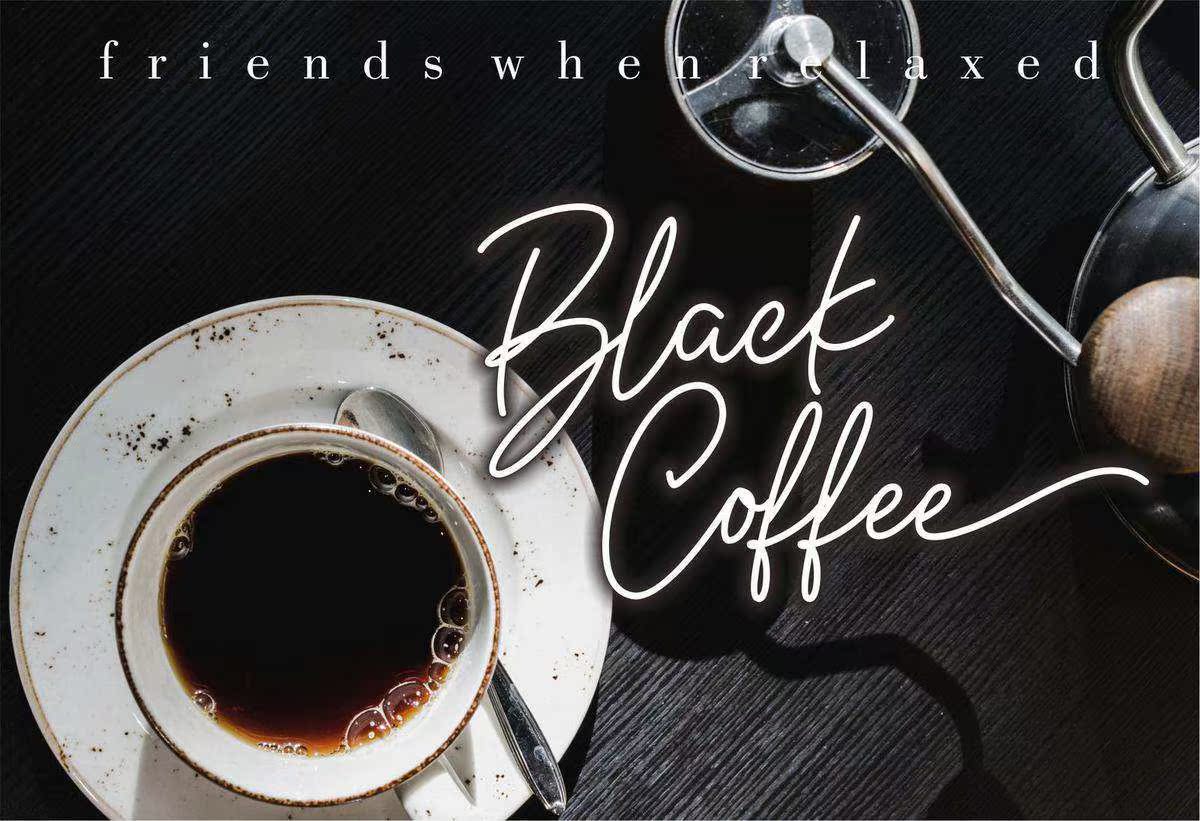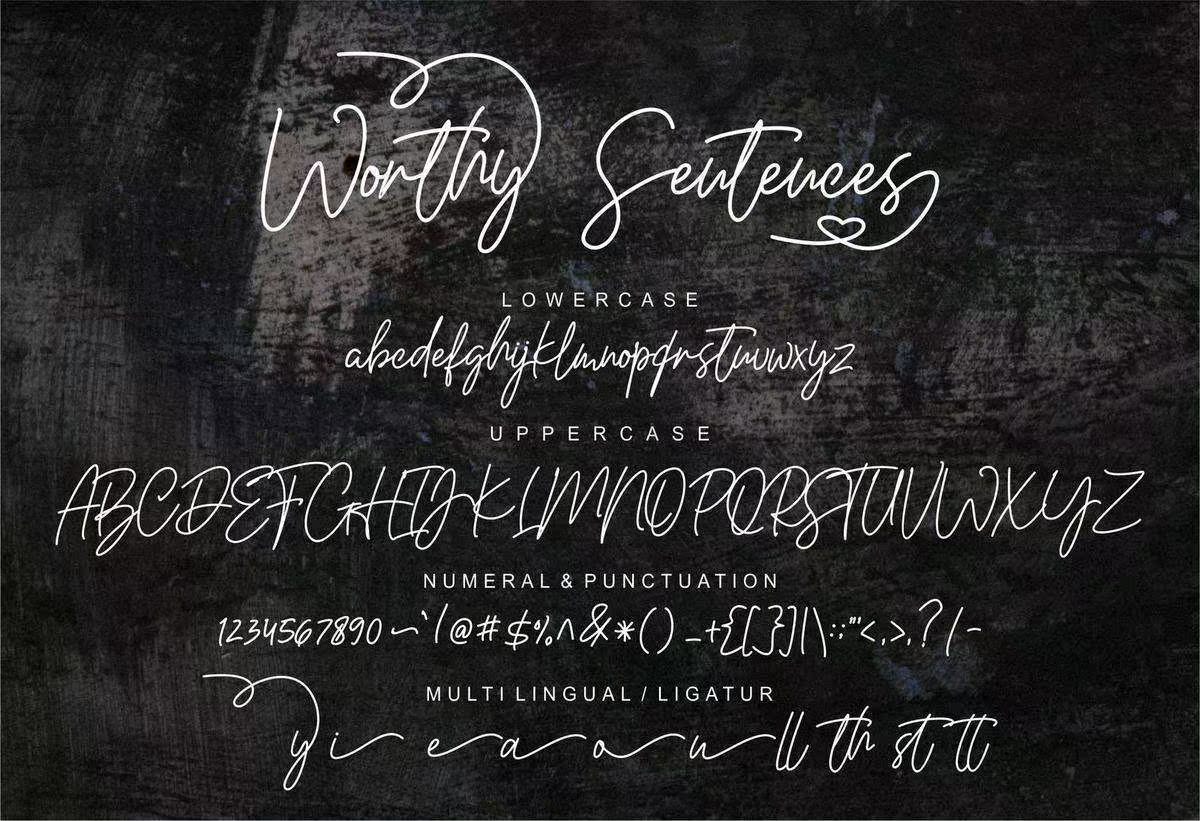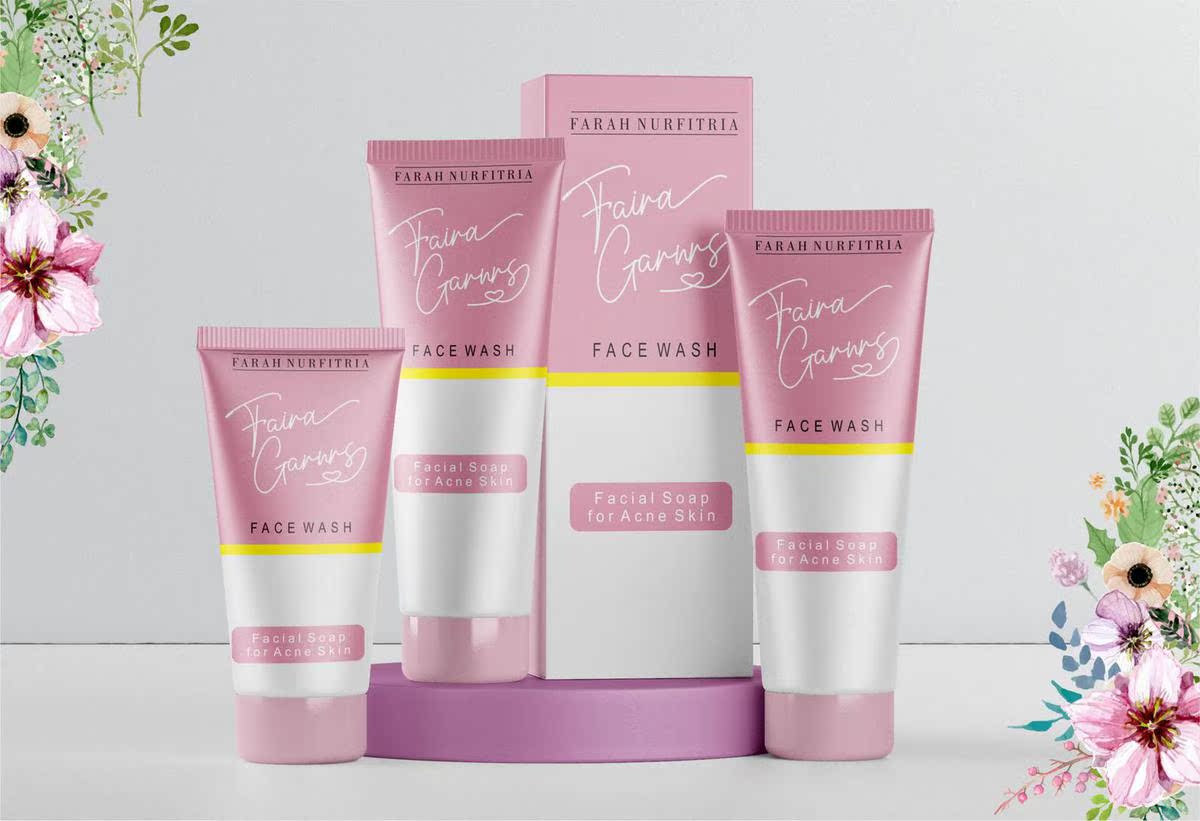
有价值的内容是直接使用鼠标的,使此字体外观完美,具有签名风格,此字体适用于看起来优雅的项目,如:婚礼、婚礼设计、品牌、社交媒体、广告、产品包装、产品设计、标签、摄影、邀请函、文具、,以及任何需要手工制作的项目。有价值的内容是直接使用鼠标的字体,使此字体外观完美且具有签名风格,此字体适用于看起来优雅的项目,如:GOS、婚礼设计、品牌、社交媒体、广告、产品包装、产品设计、标签、照片、邀请函、文具、,以及任何需要手工操作的项目。